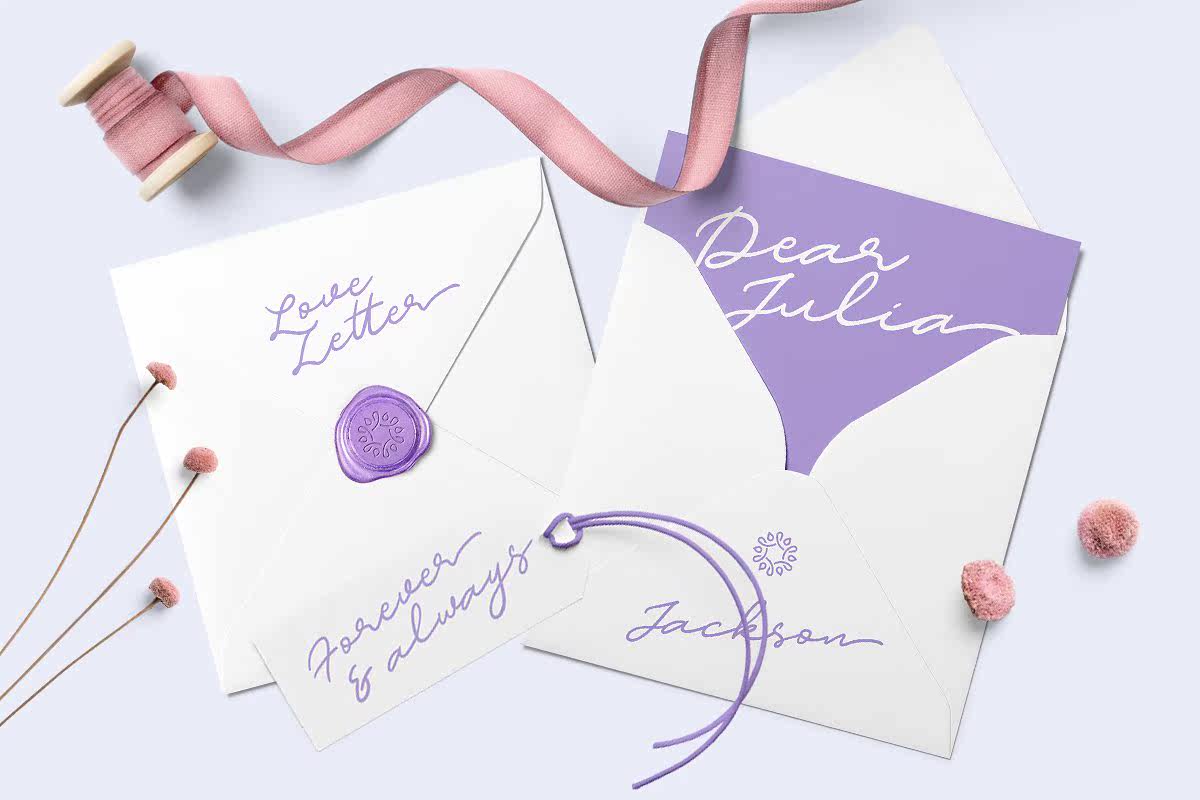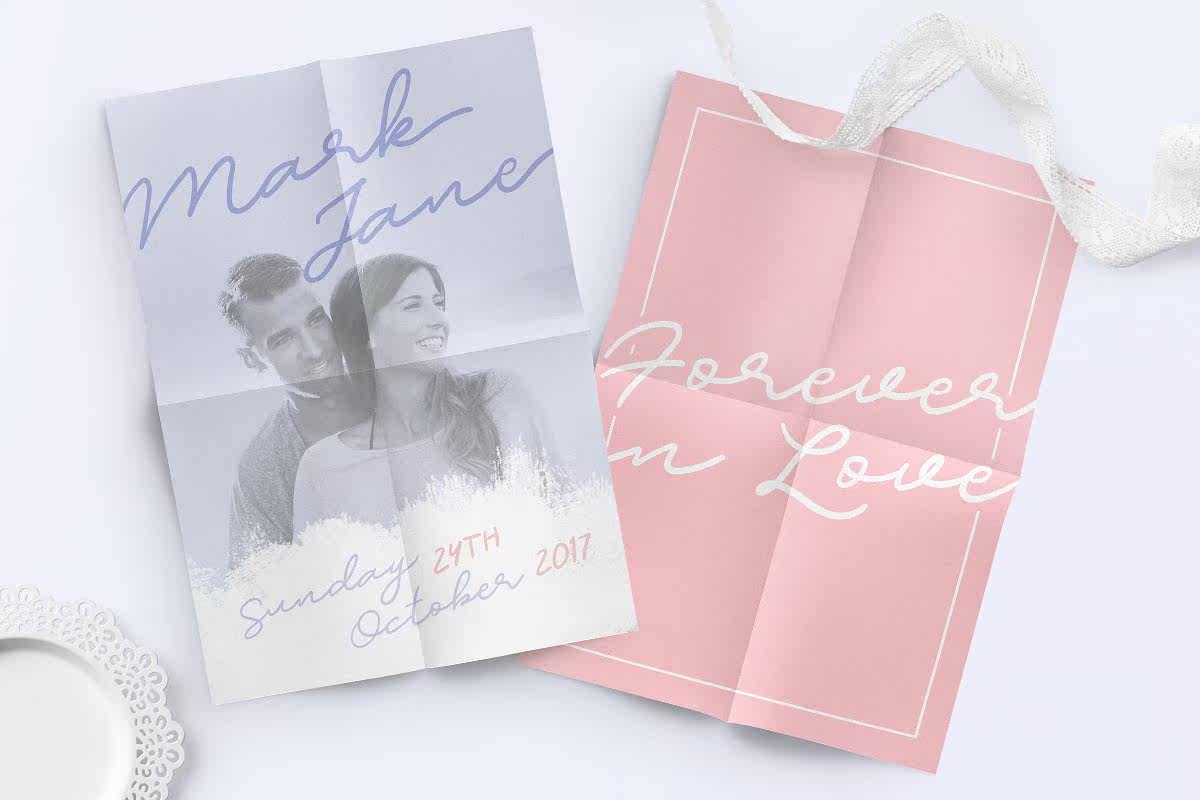
亲爱的,这是我亲爱的简。这款可爱的字体是用真实的手写体制作的,具有自然和浪漫的感觉。特别适用于签名、婚礼庆典、贺卡、标志、摄影、报价、服装设计和任何设计需求。通常,其内容包括任何开放式功能,如连字、风格设置、替换、,等等,还可以使用多种语言。亲爱的,这是我亲爱的简。这款可爱的字体是由真实的手写体制作而成,具有自然和浪漫的感觉。特别是对于签名、婚礼、问候卡、徽标、摄影、引用、装置标志和任何设计需求而言,都是完美的。通常,它的内容包括任何开放式功能,如连字、风格设置、替换、,ETC支持多语言。